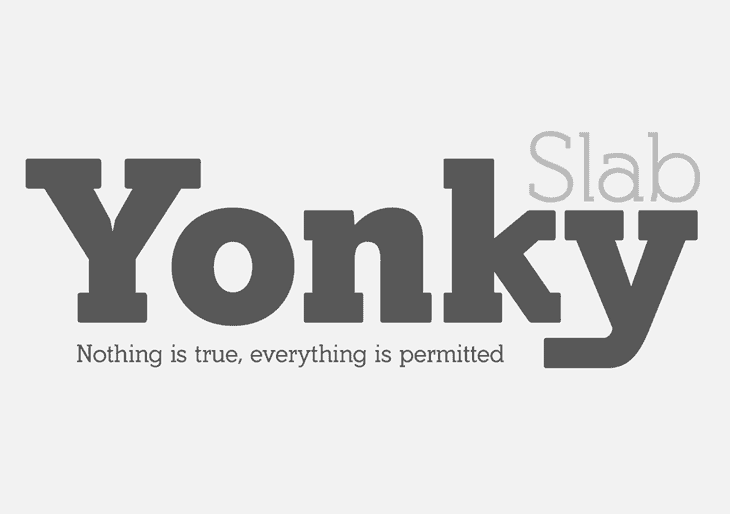
A Yonky Slab é uma família de 8 tipografias slab serif que apresento em quatro pesos diferentes: Liso, Regular, Bold e Negro, assim como suas versões verdadeiras itálicas correspondentes. Elas são herdeiras das tipografias egípcias do início do século XIX. Este conjunto de fontes é uma excelente escolha para projetos que buscam um equilíbrio entre seriedade e modernidade. Os pesos da Yonky Slab oferecem uma ampla gama de opções, desde os textos mais leves até as letras mais sólidas, o que permite a você adaptar a fonte conforme necessário para diferentes usos. Suas influências egípcias permitem que a fonte seja moderna e futurista ao mesmo tempo, ideal para ambientes de negócios ou design gráfico contemporâneos. Com Yonky Slab em seu projeto, você terá uma ferramenta poderosa capaz de criar texturas distintas e elegantes sem comprometer a legibilidade. Seja para apresentações de PowerPoint, materiais publicitários ou qualquer outro tipo de documento que exija um estilo robusto e moderno, Yonky Slab será uma fonte perfeita. Esta família de 8 tipos está disponível tanto em versão completa quanto com opções comerciais, oferecendo a você flexibilidade para integrar essa bela fonte em seus projetos.